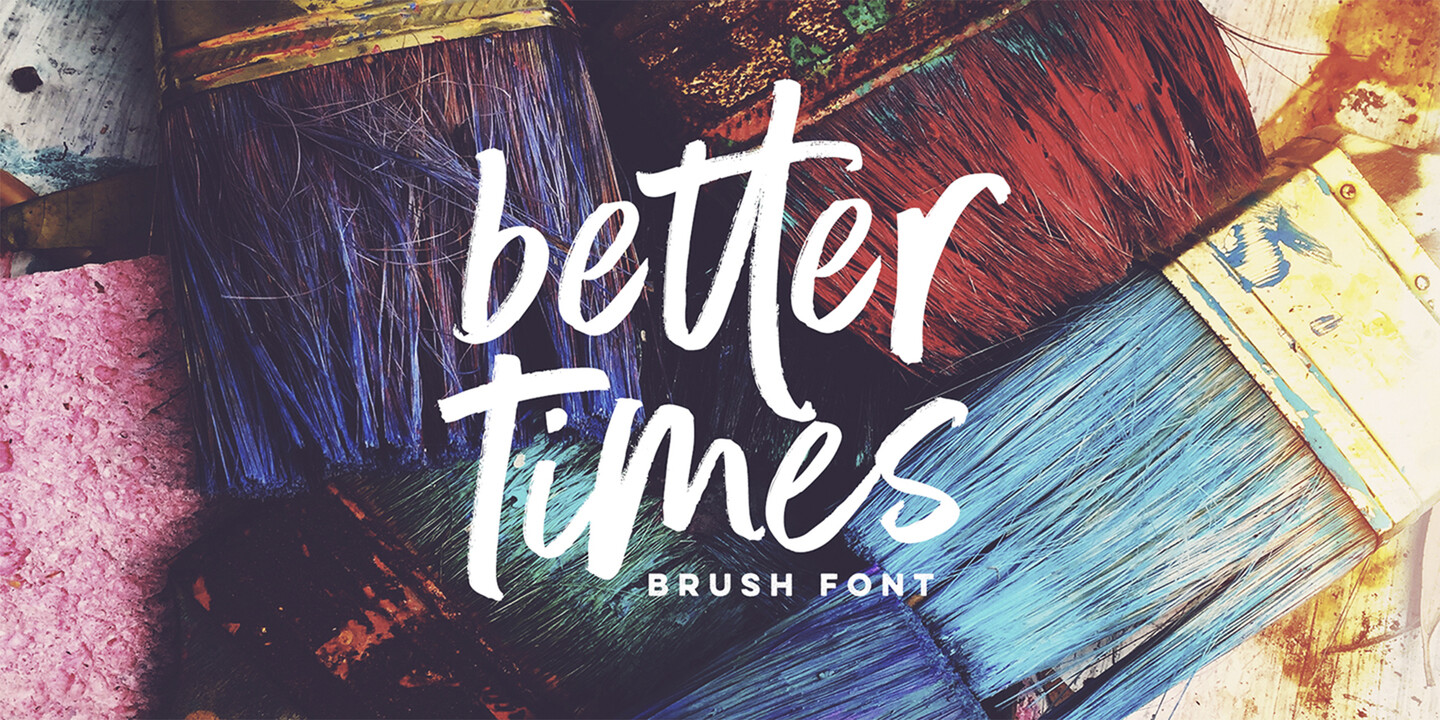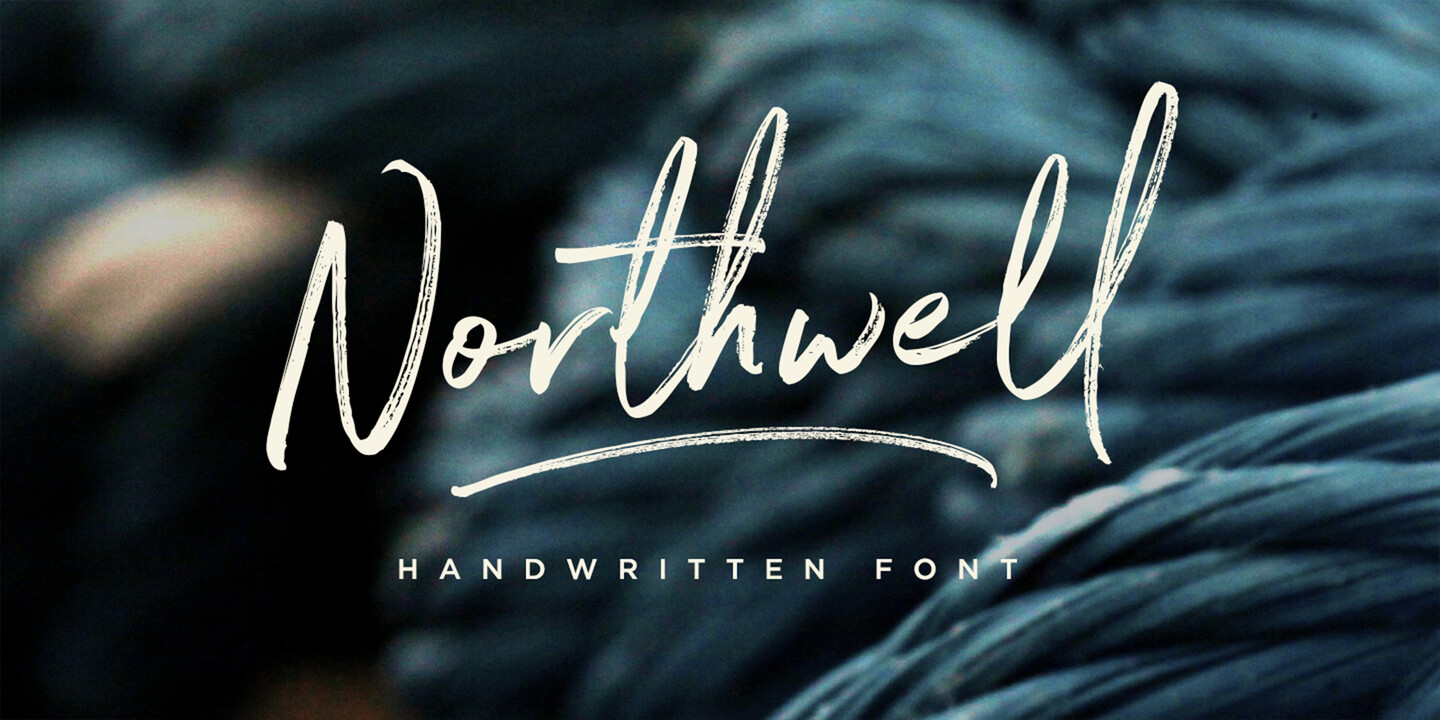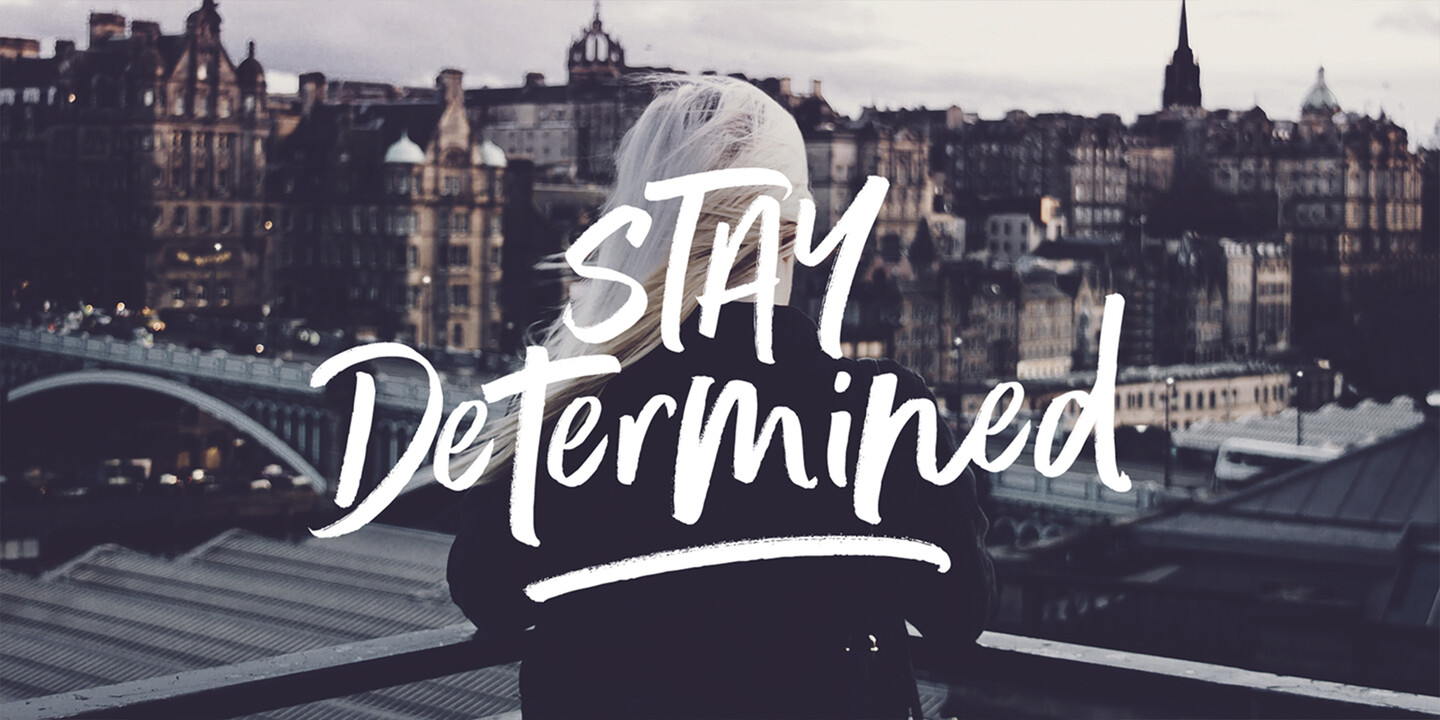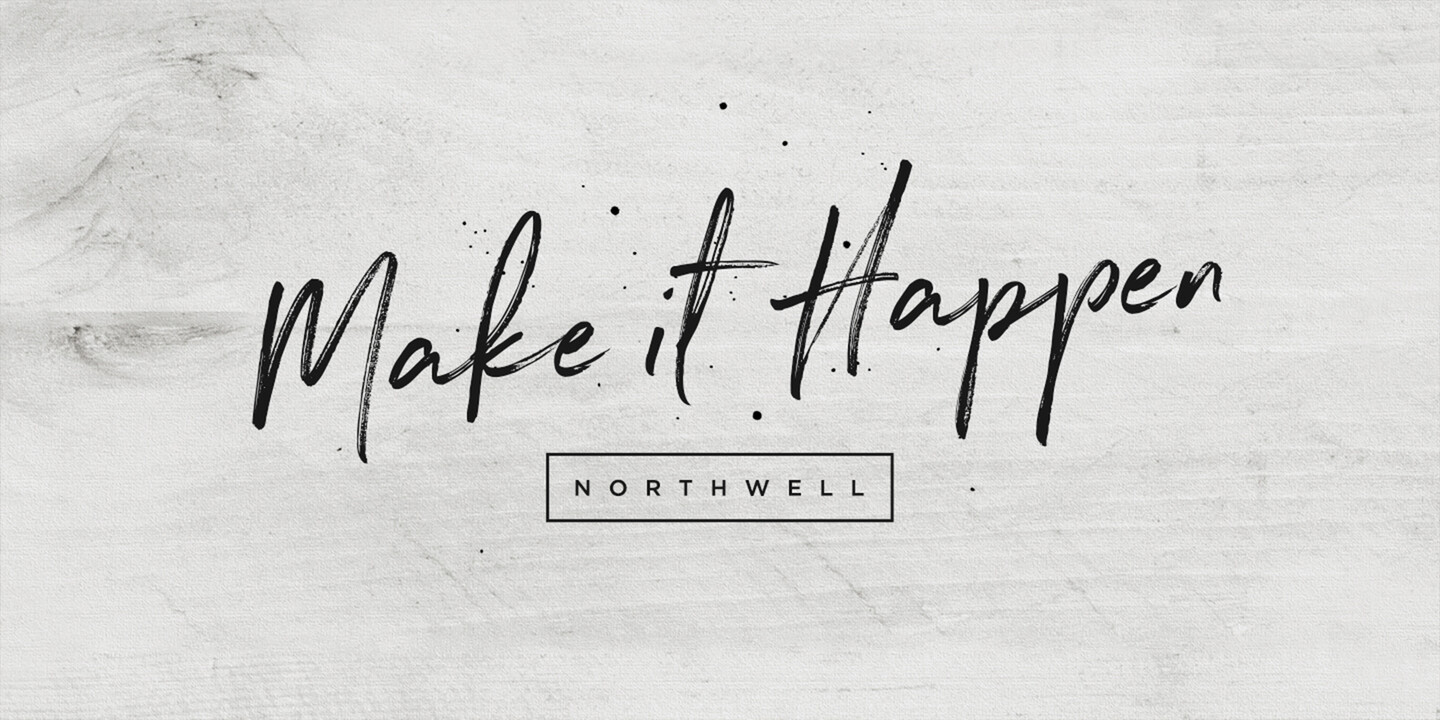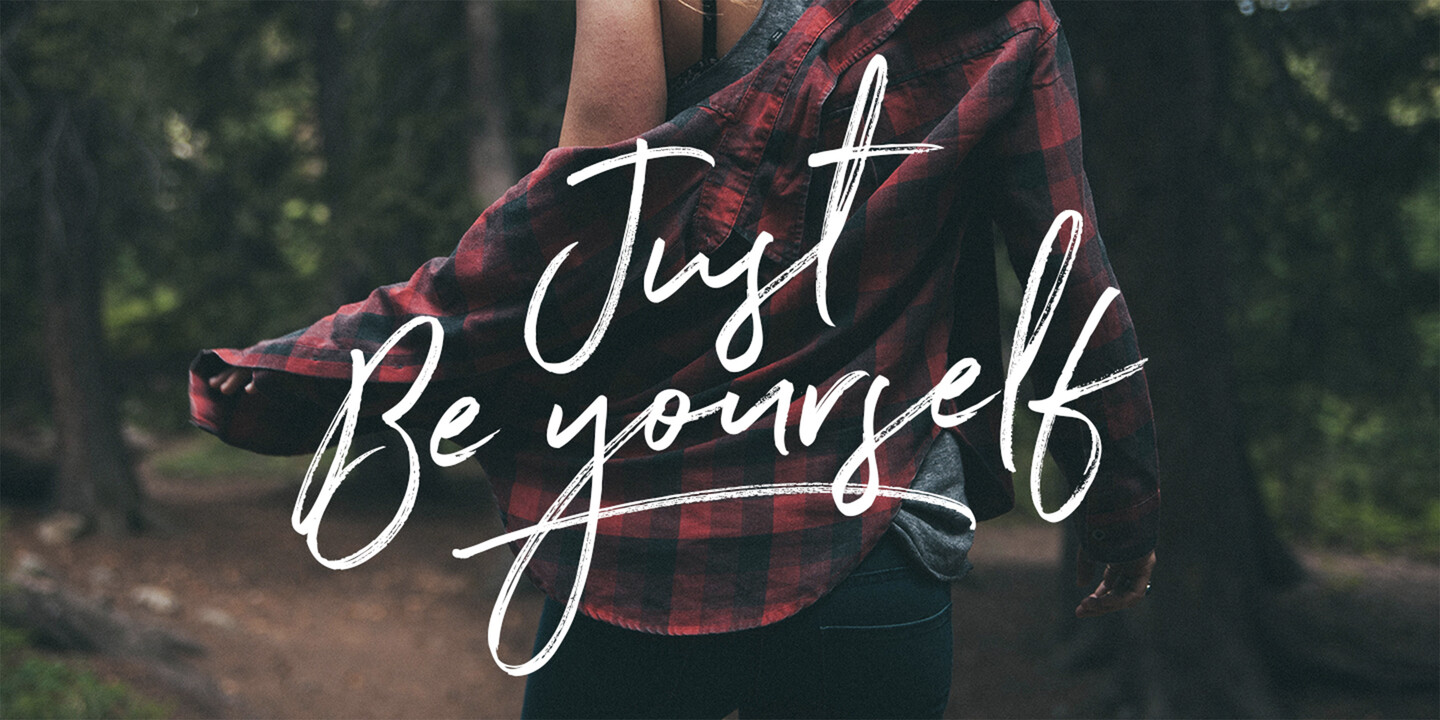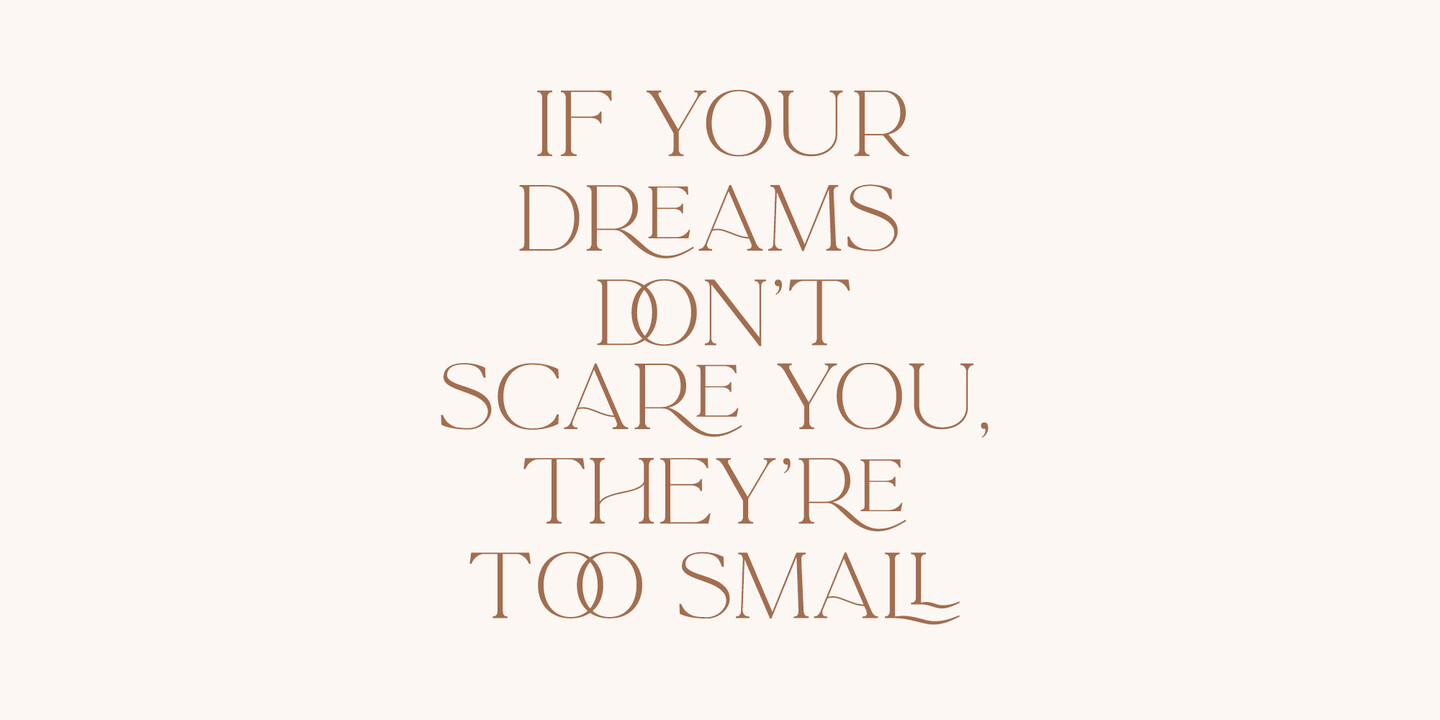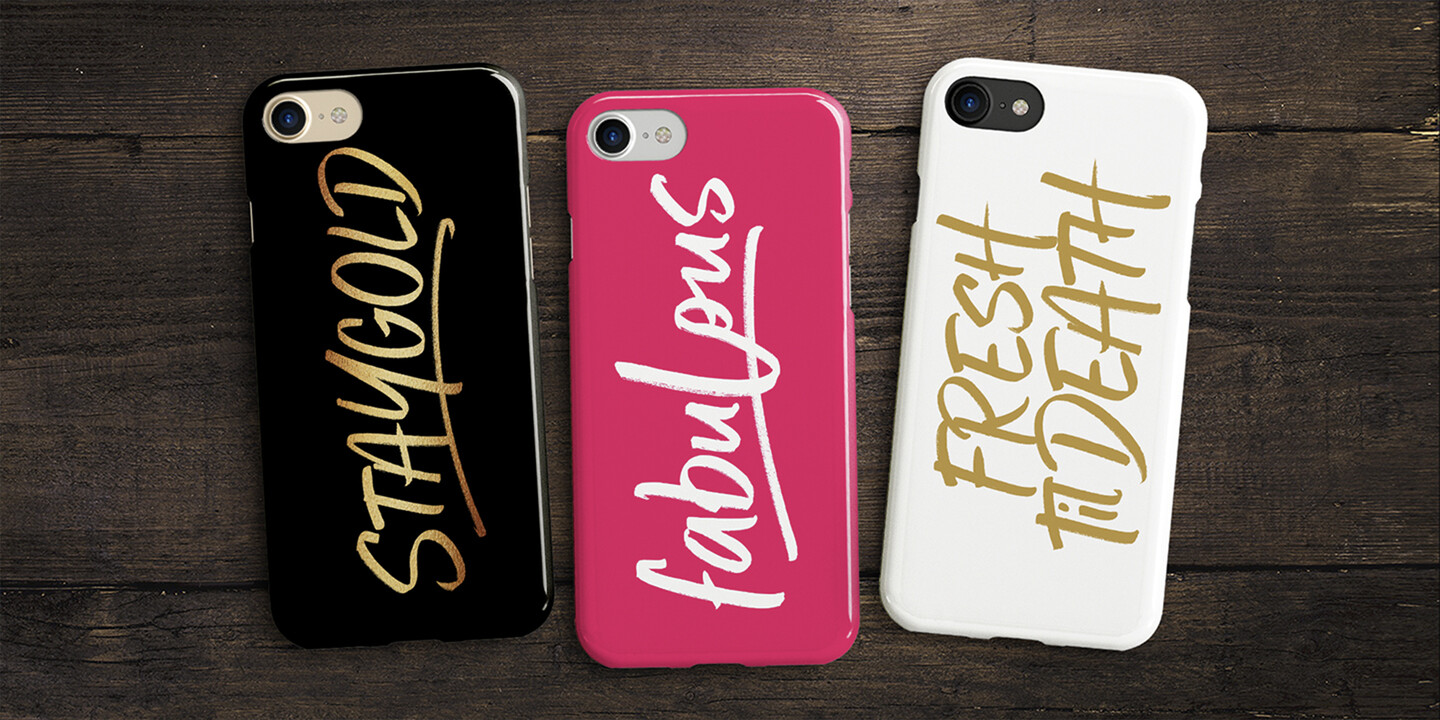
Polices de Set Sail Studios.
Set Sail Studios est une fonderie de caractères basée au Royaume-Uni, détenue et gérée par Sam Parrett. Ce qui a commencé comme un passe-temps parallèle à une carrière réussie de graphiste indépendant dans l'industrie de la musique, est rapidement devenu une passion à plein temps pour Sam, qui a franchi le pas en 2015 pour se concentrer uniquement sur ses créations police . Appliquant sa formation en design graphique pour créer des formes de lettres expressives et artisanales, le travail de Sam a connu un succès immédiat et il a depuis publié plus de 50 familles police .
Studios Set Sail populaires polices.
Ce brush police audacieux, fluide et confiant est conçu pour être facilement personnalisable avec 2 jeux de chaque lettre et un jeu bonus de 20 swashes. Oh, et sans oublier qu'elle s'affiche aussi bien en majuscules qu'en minuscules, ce qui vous offre un large éventail d'options de mise en page. Better Times est un brush police que vous pourrez utiliser et apprécier encore et encore, que ce soit pour du matériel promotionnel, des citations manuscrites, des emballages de produits, des marchandises ou des projets de marque.
Laissez-vous tenter par une typographie luxueuse avec La Luxes ; un duo classique police composé d'un élégant script et d'un serif riche en ligatures. Ces polices sont conçus pour s'associer harmonieusement et se prêtent à la création de marques, de logos, d'emballages de produits et d'invitations haut de gamme.
Northwell est une écriture manuscrite rustique et pimpante police avec un charme personnel. Avec des traits secs et rapides et un style caractéristique, Northwell est parfait pour les projets de marque, les conceptions d'articles ménagers, les emballages de produits - ou simplement comme un texte élégant superposé à n'importe quelle image d'arrière-plan. L'une des meilleures ventes de Set Sail Studios polices, Northwell a été utilisé par des marques internationales telles que Ralph Lauren - et a depuis été mis à jour pour inclure une version "propre" avec des textures remplies et des bords lisses.
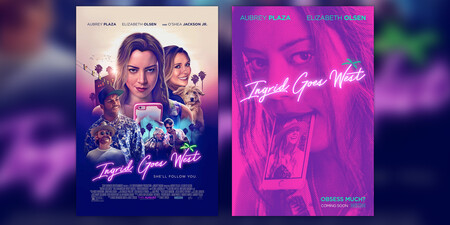
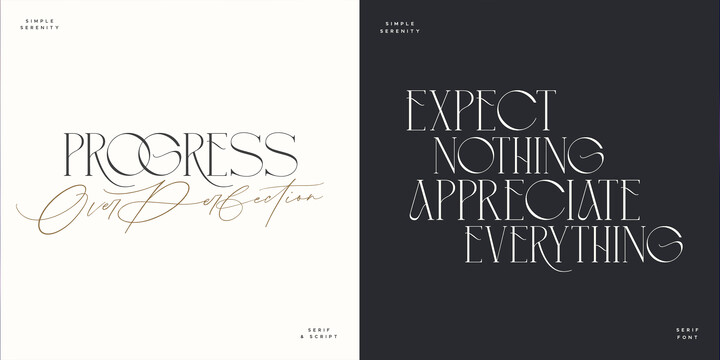
Détenu et géré uniquement par le designer Sam Parrett, basé au Royaume-Uni, Set Sail Studios se concentre sur la création de polices expressifs et accrocheurs, réalisés à la main, qui visent à bousculer le secteur et à rompre avec les formes de lettres génériques.
Réalisateur et créateur de caractères
Sam Parrett
Après avoir étudié la psychologie à l'université de Bristol, la passion de Sam pour la conception graphique est rapidement devenue son principal objectif de carrière, et il a lancé Set Sail Studios en 2011. Sam travaille depuis son bureau à la périphérie de Bristol et s'adonne au VTT et aux jeux vidéo rétro pendant son temps libre.